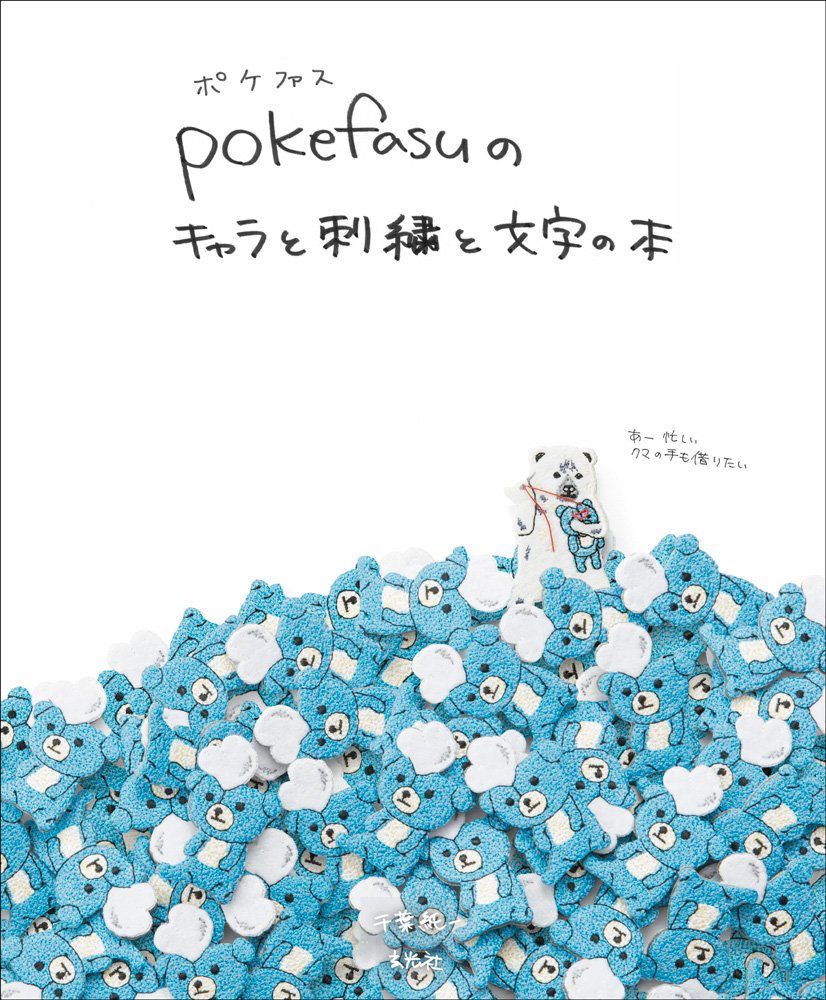
pokefasuのキャラと刺繍と文字の本
人気の刺繍ブローチ作家でありキャラクターブランドpokefasu(ポケファス)を展開する千葉純一氏初の作品集となる「pokefasuのキャラと刺繍と文字の本」が玄光社から2018年7月14日に発売される。
ちなみにブランド名のpokefasuは嘘か誠か公式HPによるとpoker faceの書き間違いらしい。
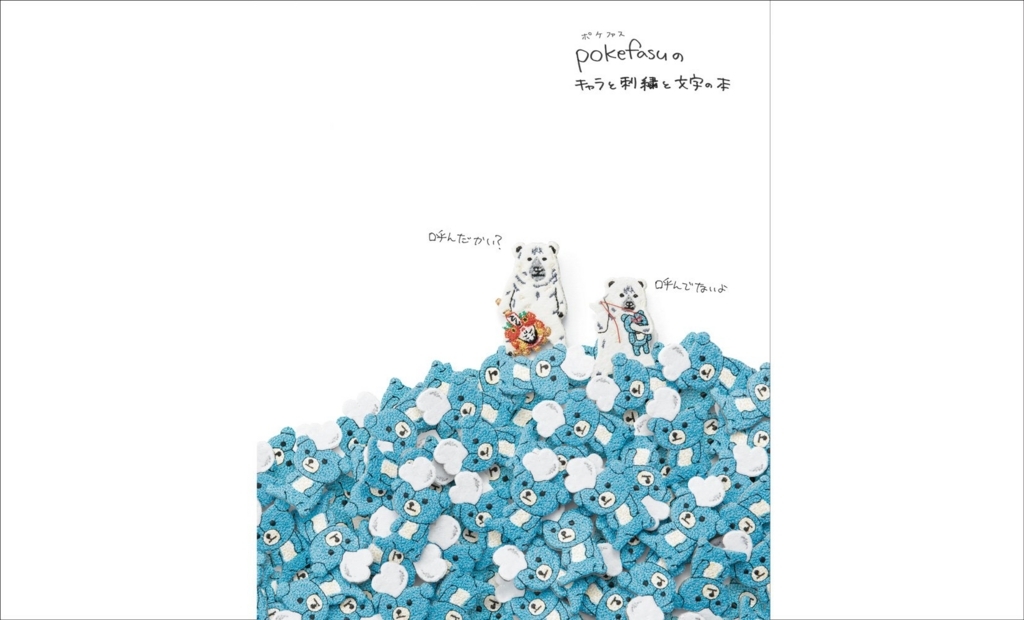
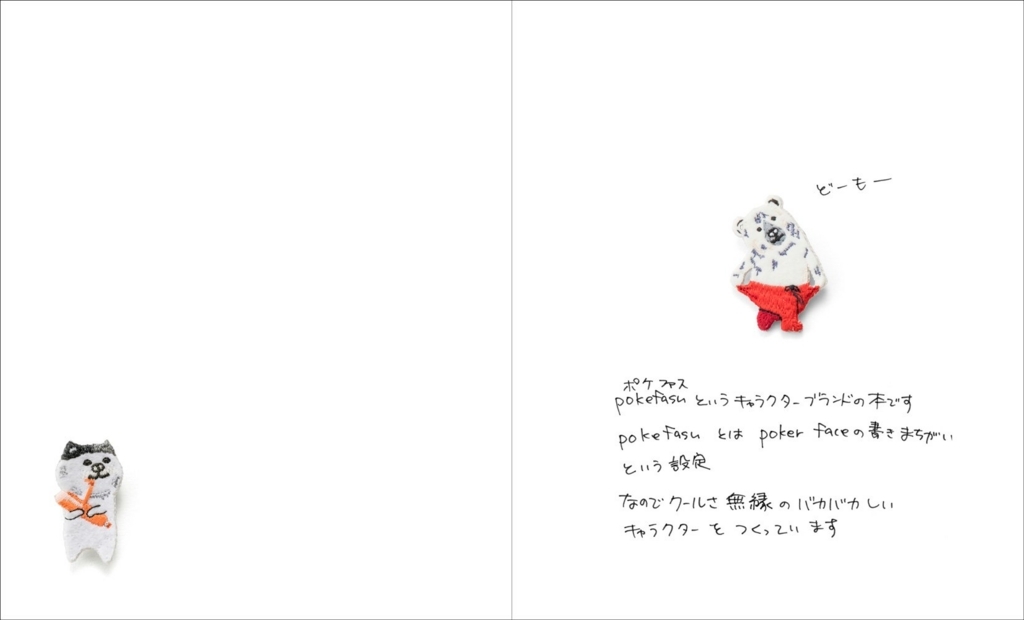
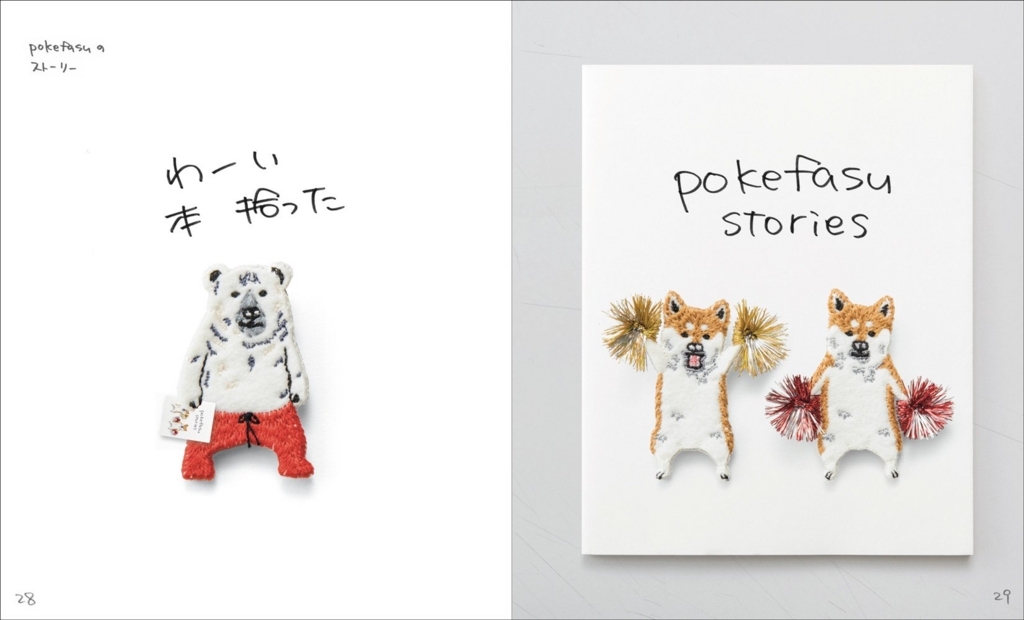
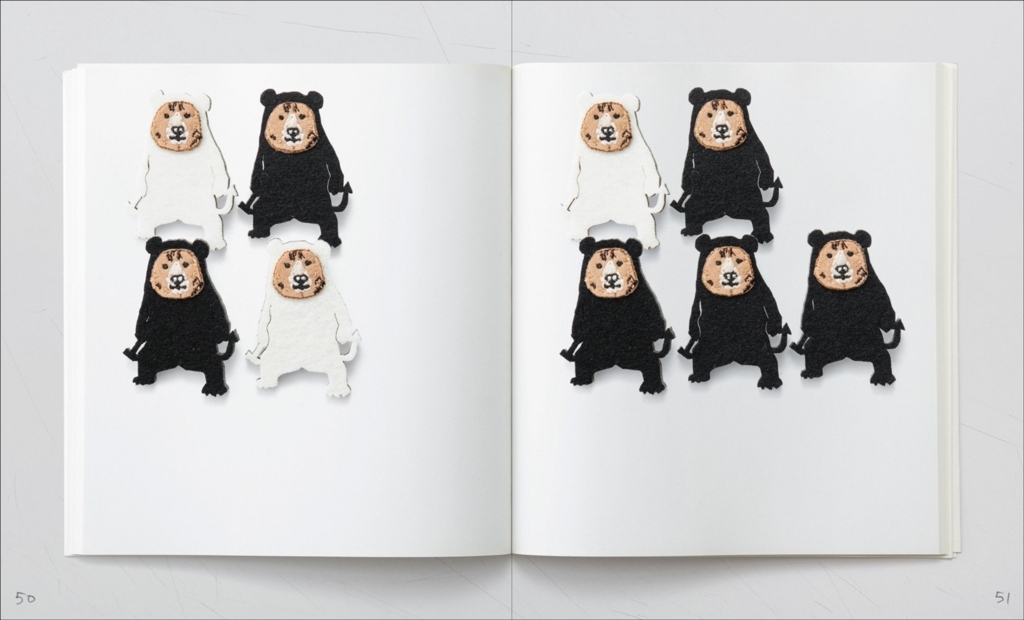
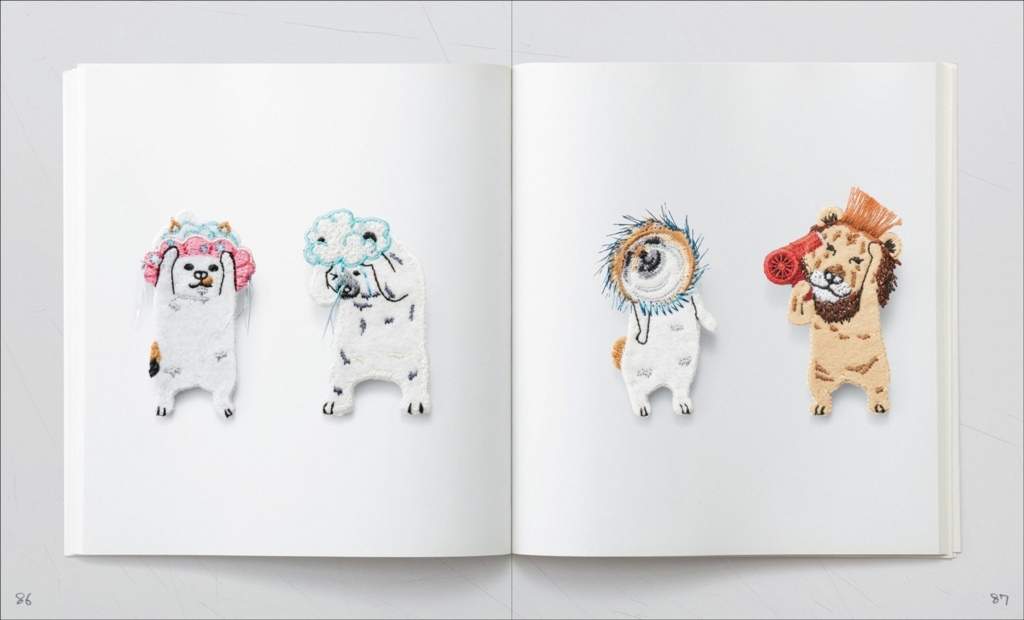
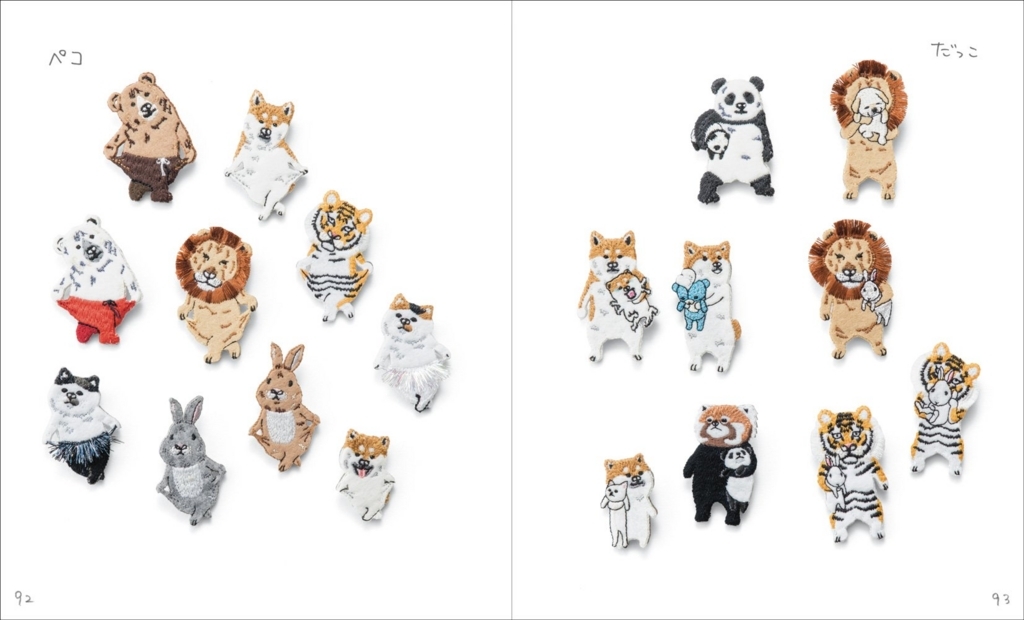
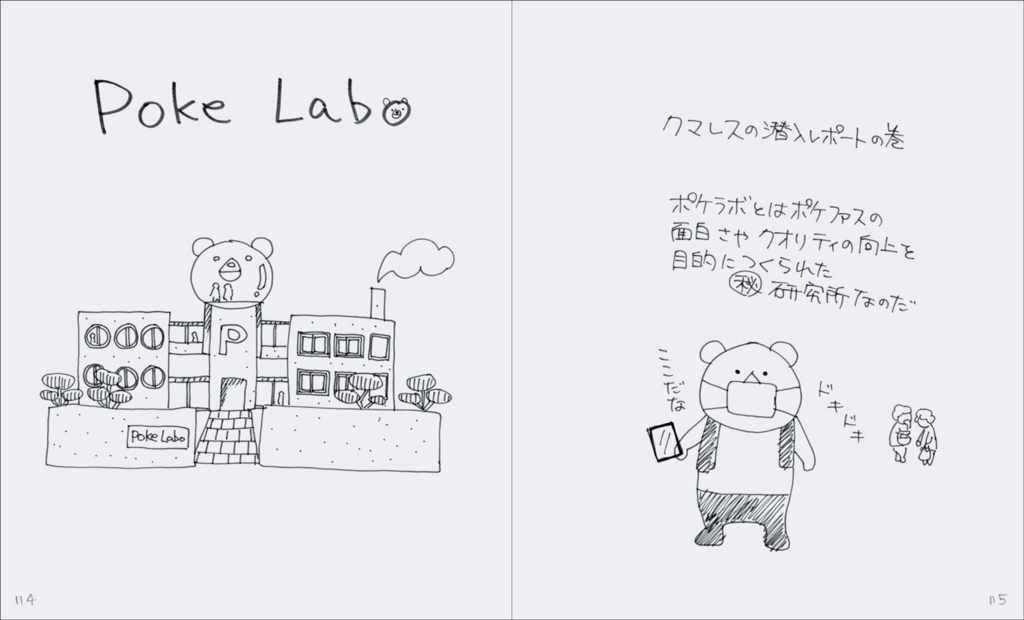
人気の刺繍ブローチ作家・キャラクターデザイナー、ポケファスによる初の作品集!
刺繍、キャラクターデザインを、絵本じたてで丸ごと収録しました。
新作キャラクター全員集合、過去の人気キャラクターたち、ブックインブック、そして刺繍ブローチのできるまでまで初公開。タイトルからノンブルまですべて手書きの世界でたった1冊の保存版ポケファス作品集です。
【目次】
pokefasuのキャラクター
pokefasuのストーリー
pokefasuのシリーズ
pokefasuのつくり方
poke labo潜入
千葉純一Profile●埼玉生まれ。
キャラクターブランド、ポケファスのデザイナー。ポケファスのキャラクターたちは刺繍ブローチのほか、マークスの手帳やツジセルのポーチ、LINEスタンプなど、数多くの雑貨ブランド等で商品化されている。